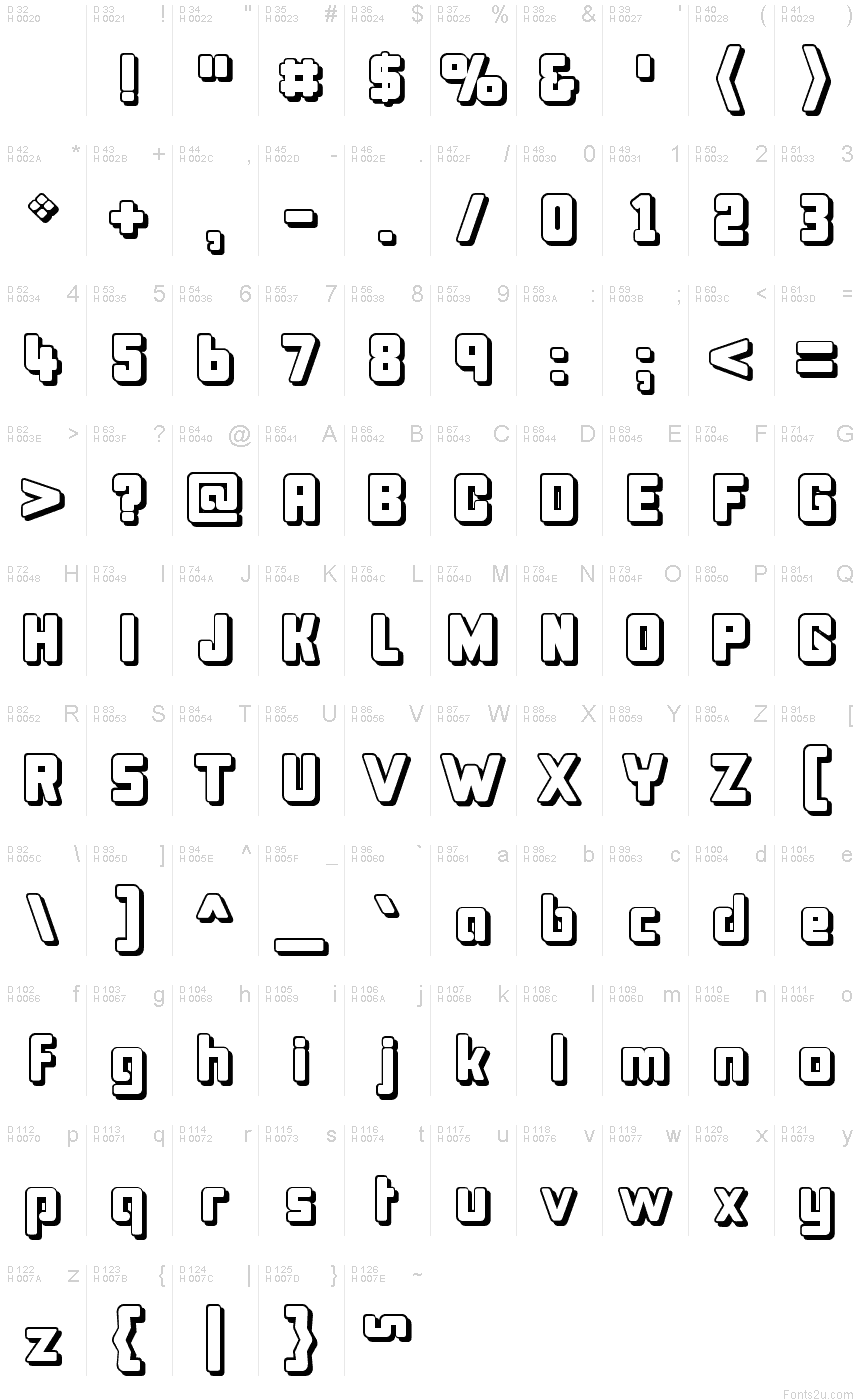
Bonk Offset od GemFonts to darmowy krój pisma w stylu komiksowym: bezszeryfowy, z wyraźnym konturem, pękatymi kształtami, zaokrąglonymi rogami i grubym cieniem, dzięki któremu każde słowo brzmi jak efekt dźwiękowy. Nadaje natychmiastowego wyrazu komiksowym kadrom, plakatom dla dzieci, tytułom gier, naklejkom i zabawnym opakowaniom przekąsek.
Bonk Offset pozostaje czytelny w krótkich nagłówkach dzięki prostym i szerokim formom, a czarne obramowanie nadaje mu dynamiczny i skoczny charakter – idealny do miniaturek na YouTube, zaproszeń na imprezy czy ogłoszeń szkolnych. Ten darmowy font najlepiej sprawdza się w dużych rozmiarach, zestawiony ze zwykłym krojem bezszeryfowym, aby jego kreskówkowa energia przyciągała całą uwagę.